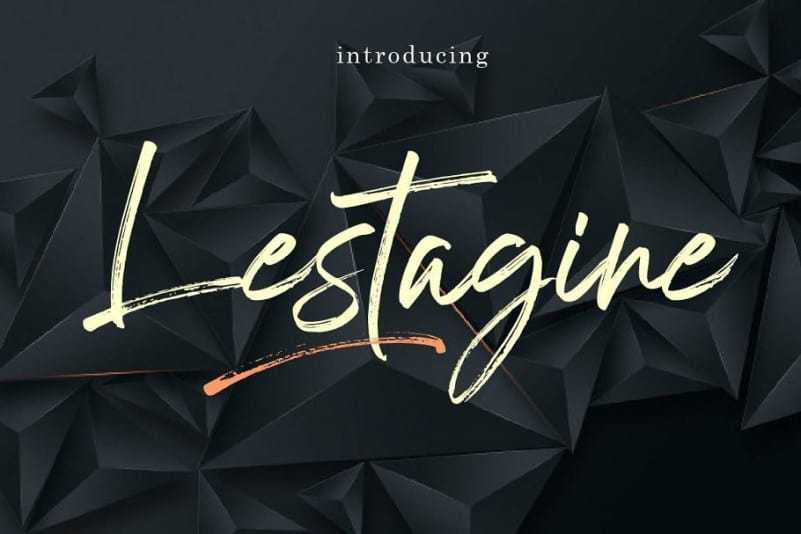
A Lestagine Brush Font é uma elegante e casual fonte feita à mão com traços grossos e finos contrastando perfeitamente. Ela foi criada pelo design vitoriano Aminmario, que usou uma caneta a ponta para dar vida ao seu trabalho originalmente manuscrito. O resultado é uma fonte script que exala estilo casual, ideal para criar identidades visuais memoráveis e slogans inovadores. Suavemente fluida, a Lestagine Brush é perfeita tanto para criações de logotipos quanto para o desenvolvimento da marca de um negócio, ou mesmo como base para frases de citação. Seja você designer web, criador de gráficos ou simplesmente amante do bom design, esta fonte será uma escolha ideal para suas necessidades, proporcionando contrastes perfeitos e harmonia em seus projetos visuais.